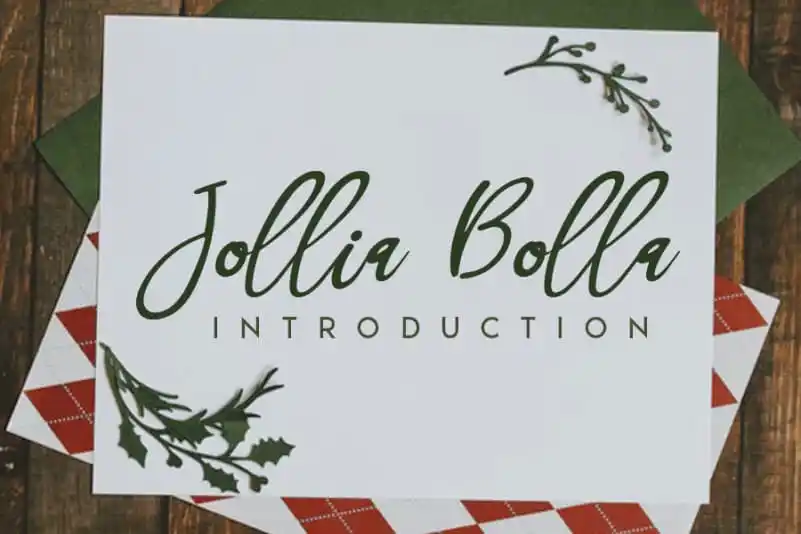
Jollia Bolla Handwritten Font – Download Grátis
A Jollia Bolla Handwritten Font é uma fonte cuidadosamente criada para quebrar as regras do padrão. Ela traz à tona a elegância com um toque de charme natural, mantendo sempre a familiaridade e simplicidade dos caracteres escritos à mão. Este tipo letra se destaca por sua estética clássica, mas nunca esquecendo que seu design é intencionalmente amigável. Esta fonte é ideal para quem busca transformar as mensagens em algo único e incomparável. Seja para um design de marca ou apenas para dar uma personalidade única ao texto da sua página web, Jollia Bolla Handwritten Font oferece a liberdade criativa que tanto adoramos na escrita à mão. Combinada com outros elementos gráficos adequados, pode-se criar designs impecáveis e surpreendentes. Seja você um designer ou simplesmente quem curte estilos artesanais em seus projetos de design, Jollia Bolla Handwritten Font é a escolha certa para deixar suas criações ainda mais memoráveis.